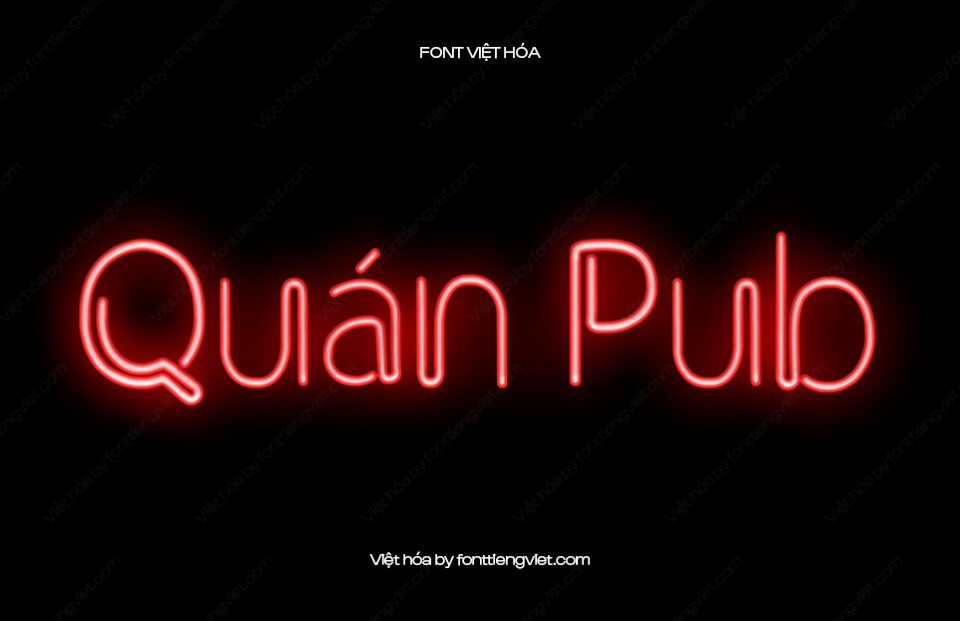
Font Việt hóa 1FTV VIP Clip – Kiểu Neon: Sự Lựa Chọn Hoàn Hảo Cho Thiết Kế Hiện Đại
Trong thế giới đồ họa kỹ thuật số hiện nay, việc lựa chọn một bộ Font Chữ phù hợp đóng vai trò then chốt trong việc tạo nên dấu ấn riêng cho tác phẩm. Font Việt hóa 1FTV VIP Clip – Kiểu Neon nổi lên như một giải pháp tuyệt vời cho những ai đang tìm kiếm phong cách rực rỡ và đầy năng động. Bộ font này không chỉ đơn thuần là các ký tự mà còn mang trong mình hơi thở của nhịp sống đô thị về đêm, nơi những ánh đèn neon lung linh chiếu sáng khắp các con phố.
Đặc điểm nổi bật của Font Việt hóa 1FTV VIP Clip – Kiểu Neon
Thiết kế mô phỏng ánh sáng nghệ thuật
Đúng như tên gọi, Font Việt hóa 1FTV VIP Clip – Kiểu Neon được thiết kế dựa trên cấu trúc các ống đèn neon uốn lượn. Các đường nét thanh mảnh nhưng chắc chắn giúp tạo ra hiệu ứng phát sáng chân thực khi kết hợp cùng các bảng màu gradient rực rỡ như hồng, xanh dương hay tím điện tử. Đây là lựa chọn lý tưởng cho các poster ca nhạc, bìa album hoặc các video clip nghệ thuật cần sự bứt phá về thị giác.
Khả năng hiển thị và tính tương thích
Điểm cộng lớn nhất của bộ font này chính là việc đã được Việt hóa hoàn chỉnh. Người dùng không còn phải lo lắng về lỗi hiển thị các ký tự tiếng Việt đặc trưng như dấu hỏi, dấu ngã hay các ký tự đặc biệt. Font chữ này tương thích tốt với hầu hết các phần mềm thiết kế chuyên nghiệp như Adobe Photoshop, Illustrator cho đến các ứng dụng đơn giản trên điện thoại.
Ứng dụng Font Việt hóa 1FTV VIP Clip – Kiểu Neon trong thực tế
Bộ font này cực kỳ linh hoạt trong nhiều lĩnh vực khác nhau. Trong môi trường học đường, các bạn học sinh có thể sử dụng để làm tiêu đề cho các bài thuyết trình, giúp nội dung trở nên lôi cuốn và hiện đại hơn. Trong kinh doanh, các quán cà phê hay cửa hàng thời trang trẻ trung cũng thường dùng kiểu chữ này để thiết kế bảng hiệu điện tử hoặc hình ảnh quảng bá trên mạng xã hội.
Kết luận về bộ font nghệ thuật
Tóm lại, nếu bạn đang tìm kiếm một công cụ để nâng tầm thẩm mỹ cho dự án của mình thì đừng bỏ qua Font Miễn Phí, Font Việt Hóa, Font Việt hóa 1FTV VIP Clip – Kiểu Neon. Với sự kết hợp giữa nét cổ điển của đèn neon và công nghệ việt hóa hiện đại, sản phẩm này chắc chắn sẽ mang lại hiệu quả bất ngờ cho mọi sản phẩm sáng tạo của bạn.